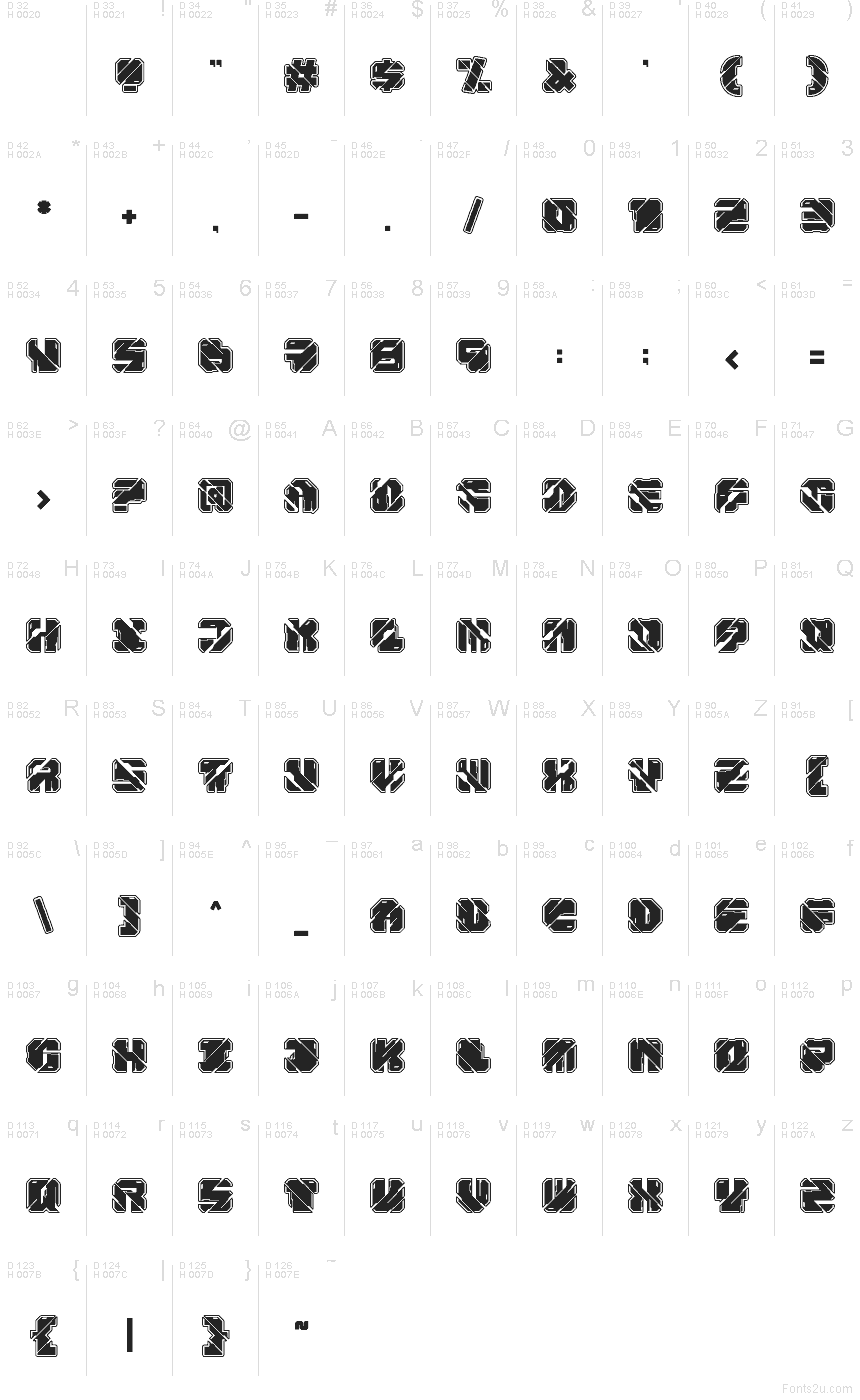
Space Sparkle Two od Putracetol Studio je bezplatné, futuristické display písmo definované ostrými, zkosenými obrysy, díky nimž písmena připomínají sci-fi panely. Opakované šikmé řezy a vsazené lemování vytvářejí vrstvený, mechanický rytmus, takže design působí spíše jako inženýrský výtvor než jen geometrický prvek.
Tato struktura dodává krátkým titulkům na síle v herních logách, e-sportové grafice, technologických plakátech, streamovacích bannerech i na obalech pro gadgety nebo doplňky. Hodí se také pro nadpisy v rozhraní a eventový branding, kde segmentovaný rám může bez nutnosti dalších efektů připomínat HUD grafiku, obtisky nebo nápisy inspirované vozidly.